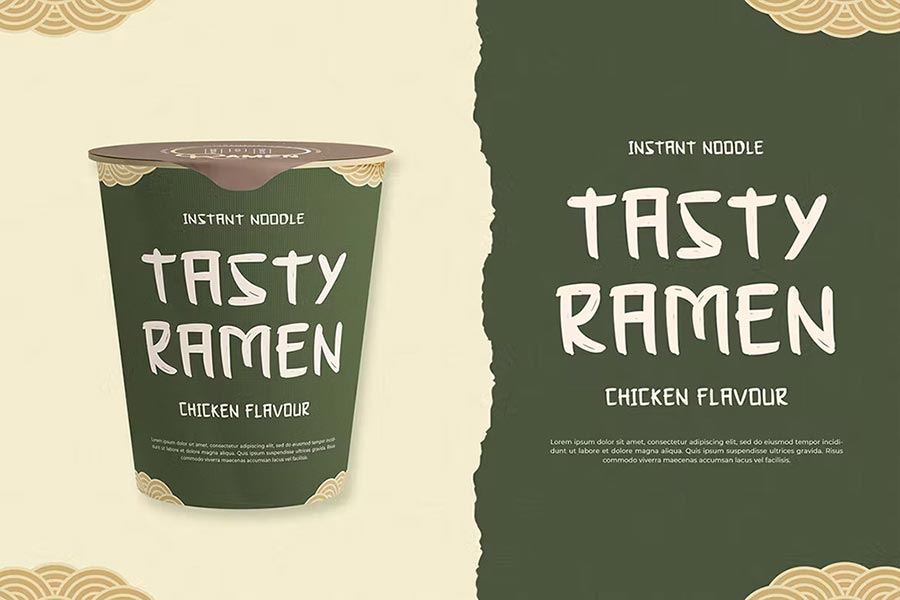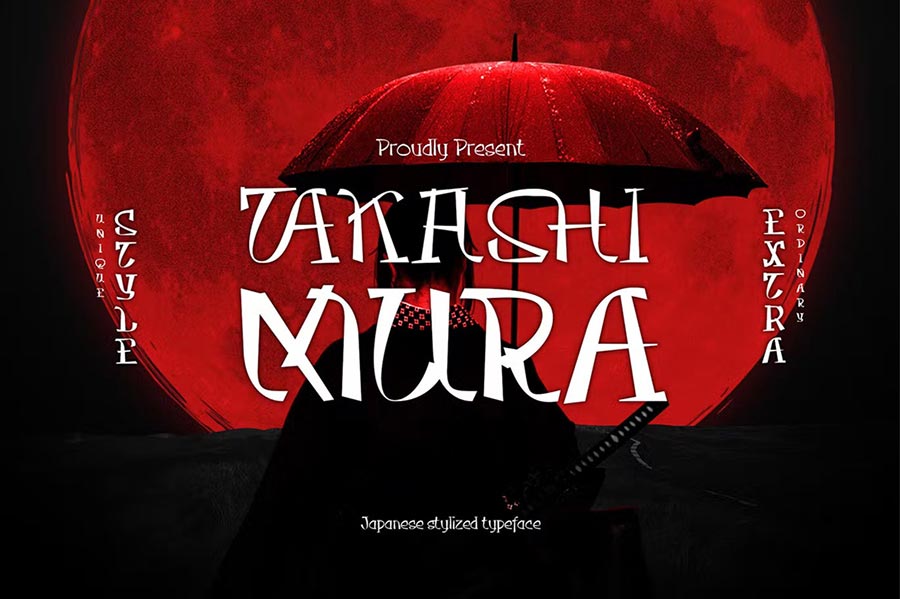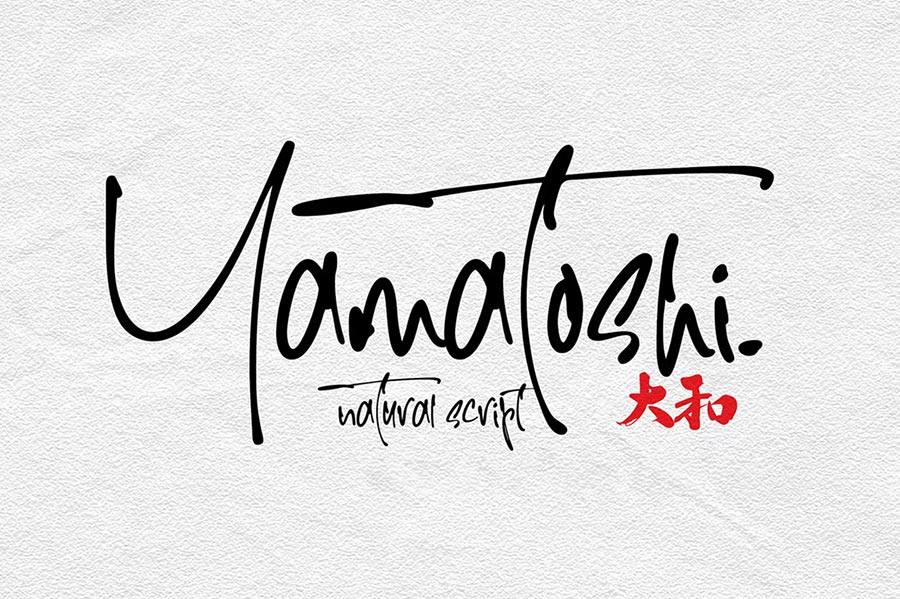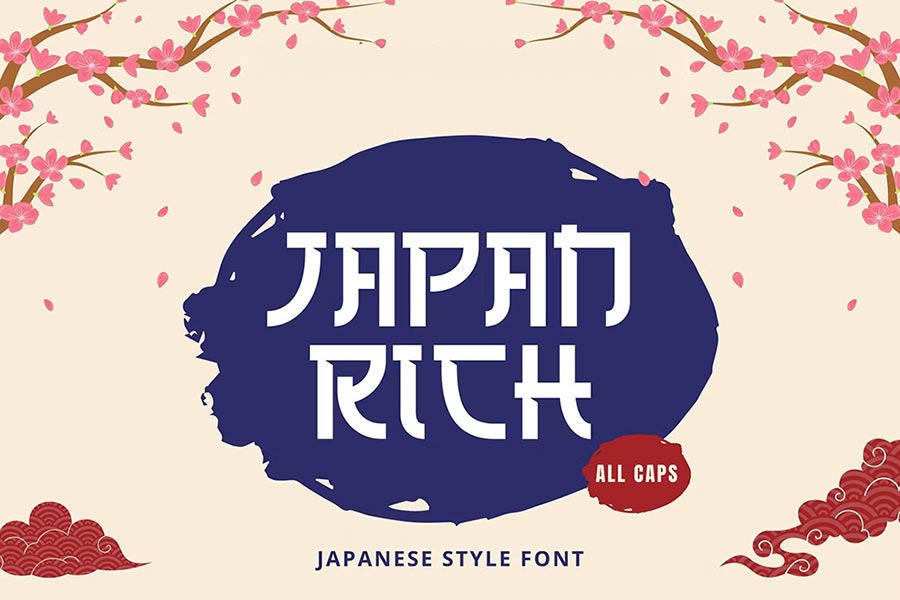
Trong lĩnh vực thiết kế đồ họa, font chữ đóng vai trò quan trọng trong việc tạo nên phong cách và bản sắc riêng cho các sản phẩm sáng tạo. Hiểu rõ nhu cầu này, Sadesign đã chính thức giới thiệu và chia sẻ bộ cài đặt font chữ Nhật cổ, mang đến một nguồn tài nguyên giá trị cho các nhà thiết kế và những người yêu thích văn hóa Nhật Bản.
1. Giới thiệu về Font Chữ Nhật Cổ
Font chữ Nhật cổ là một dạng thiết kế đặc biệt, lấy cảm hứng từ các nét chữ truyền thống của Nhật Bản trong các tác phẩm thư pháp, văn kiện cổ và nghệ thuật bản in Ukiyo-e. Những font chữ này không chỉ mang tính thẩm mỹ cao mà còn truyền tải được tinh thần văn hóa đặc sắc của xứ sở hoa anh đào.
Với sự kết hợp giữa sự mềm mại và mạnh mẽ trong từng nét chữ, bộ font này phù hợp để sử dụng trong nhiều dự án như thiết kế poster, logo, bao bì sản phẩm, hoặc các ấn phẩm liên quan đến chủ đề văn hóa Á Đông.
2. Tính Năng Nổi Bật của Bộ Font Chữ Nhật Cổ
Liệt kê một số tính năng nổi bật của bộ font chữ Nhật cổ, cụ thể:
Đa dạng kiểu dáng: Bộ font bao gồm nhiều kiểu chữ khác nhau, từ phong cách thư pháp mềm mại đến các nét chữ vuông vắn, mạnh mẽ.
Chất lượng cao: Các font chữ được thiết kế với độ phân giải cao, đảm bảo hiển thị rõ nét trên mọi kích thước và nền tảng.
Tôn vinh văn hóa: Mỗi font chữ đều được thiết kế cẩn thận để giữ nguyên tinh thần truyền thống của Nhật Bản, đồng thời phù hợp với xu hướng thiết kế hiện đại.
4. Ứng Dụng Thực Tiễn
Bộ font chữ Nhật cổ không chỉ giới hạn trong việc sử dụng cho các dự án thiết kế đồ họa mà còn có thể áp dụng trong các lĩnh vực khác như:
- Thiết kế thiệp mời, banner sự kiện liên quan đến chủ đề Nhật Bản.
- Trang trí nội dung sách, tạp chí hoặc blog chuyên về văn hóa Á Đông.
- Phát triển thương hiệu cho các doanh nghiệp kinh doanh sản phẩm Nhật Bản.
5. Kết Luận